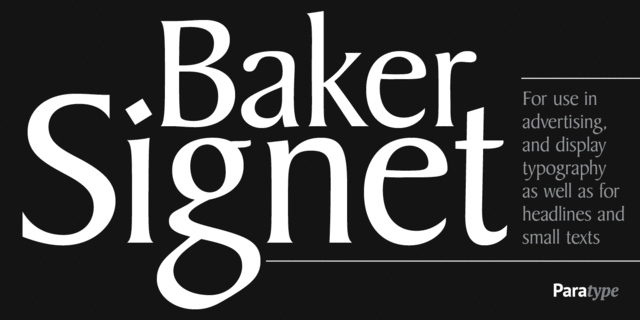
Версия фирмы Битстрим шрифта Бейкер Сигнет, созданного известным каллиграфом Артуром Бейкером для компании VGC в 1965 году. Шрифт классических форм с тонким, но эффектным каллиграфическим оттенком и едва наметившимися засечками на концах штрихов. Предназначен для титульных и акцидентных работ, рекламы и набора небольших текстов. Кириллическая версия разработана Евгением Садко и выпущена фирмой ПараТайп в 2008 году.
дорогой, элитный, благородный, традиционный, качественный, мастерский, культурный, эстетичный, изящный, роскошный, художественный, знаменитый, драгоценный, уникальный, оригинальный, отборный, красивый, комильфо, богатый, сексуальный, джентльменский, фантастичный, пафосный, старинный, исторический, имперский, сакральный
искусство, художник, музыка, архитектура, скульптура, опера, поэзия, косметика, здоровье, красота, еда, алкоголь, коньяк, премиум, ресторан, отель, гостиница, шоколад, украшение, ювелир, серебро, драгоценности, сервировка, роскошь, виски, мода, краска, памятник, гигиена, чистота, чай, часы, комильфо, кофе, мемориал, живопись, трофей, награда, бутик, концерт, Библия, вино, закат Стилистика:
Хит 1960-х Этот шрифт в логотипах:
Coca-cola, Hankey Bannister, Dermacol, Armstreet